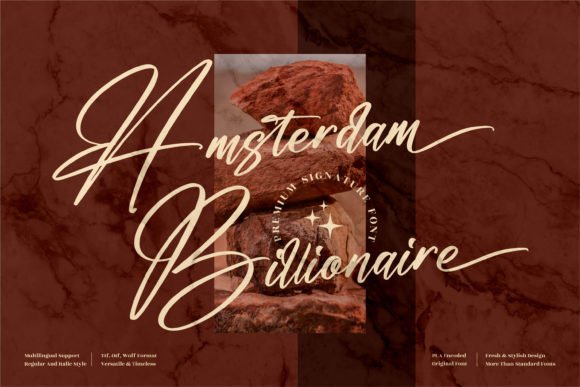
Creativefabrica Amsterdam Billionaire Font 2021
[Creativefabrica] Amsterdam Billionaire Font (2021)
Amsterdam Billionaire - это современный и элегантный шрифт.
Он идеально подходит для проектов, в которых необходим фирменный вкус, таких как брендинг, дизайн домашней утвари, кружки, цитаты, обложки книг, именные карточки, карточки для встреч и многое другое!